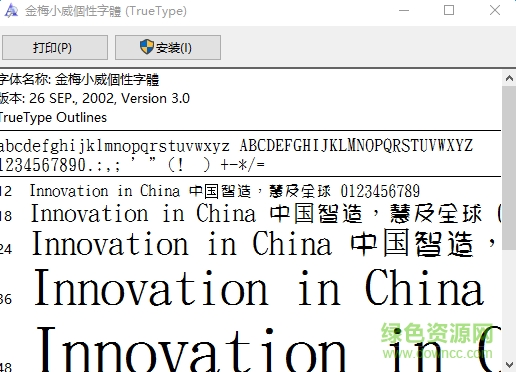
金梅小威個(gè)性體
金梅小威個(gè)性字體是金梅字庫(kù)中比較有特色的一款字體,就像它的名字一樣是很有個(gè)性的,可以用于很多方面,書(shū)本印刷、影視設(shè)計(jì)、廣告設(shè)計(jì)等都可以,歡迎有需要的朋友來(lái)綠色資源網(wǎng)下載。
金梅小威個(gè)性體是一款比較不一樣的字體,它不像有些字體那樣呆板,它是很有活力的,而且很好看,屬于那種很耐看的字體,大家肯定也會(huì)喜歡這款字體的。